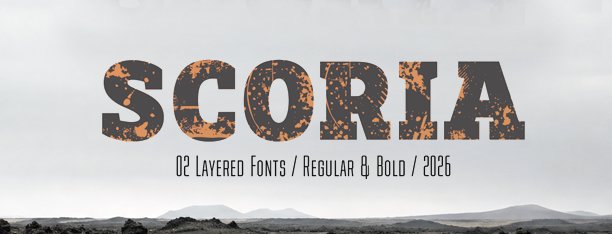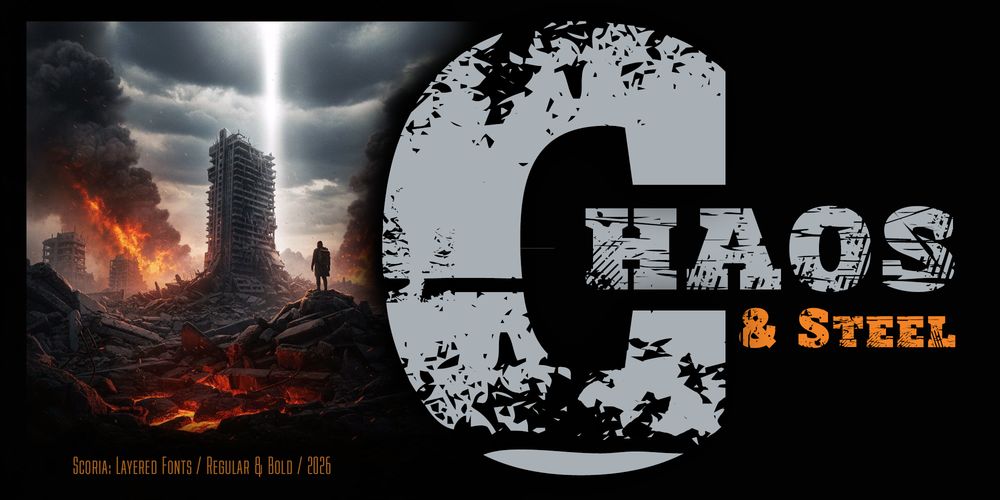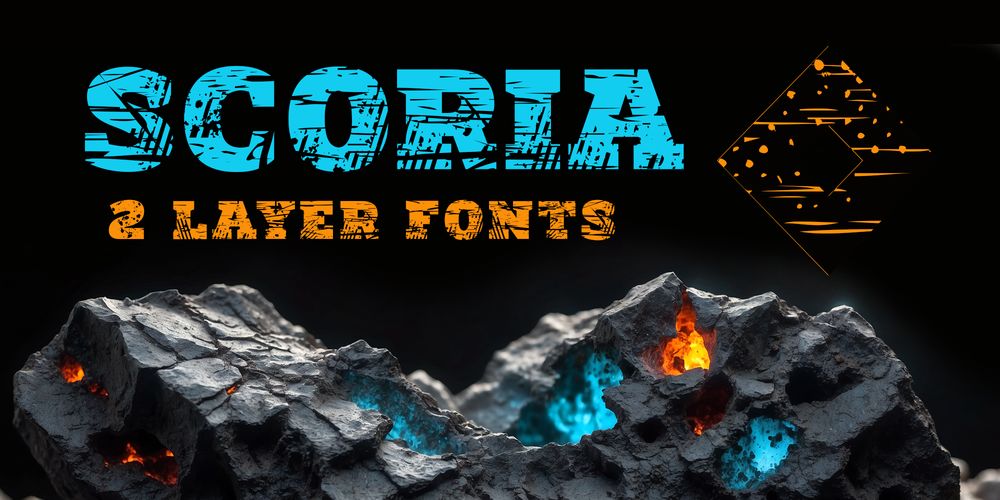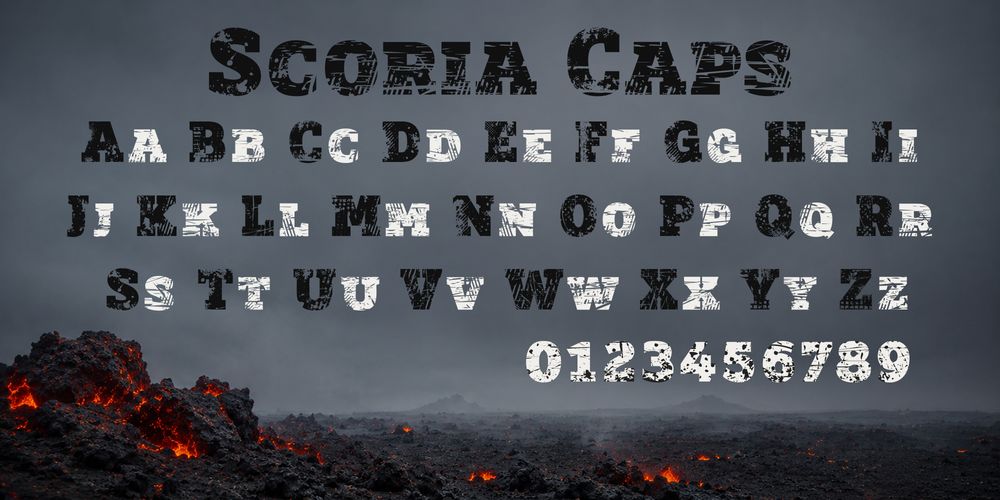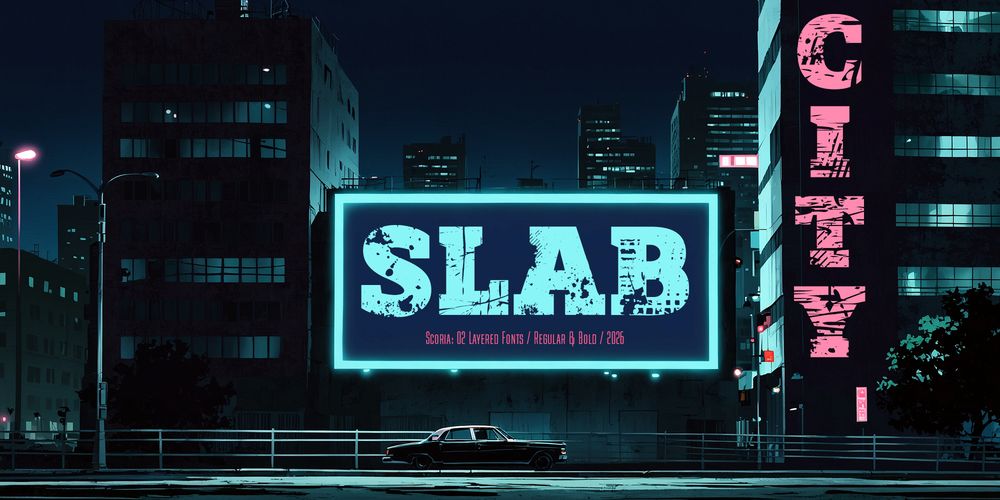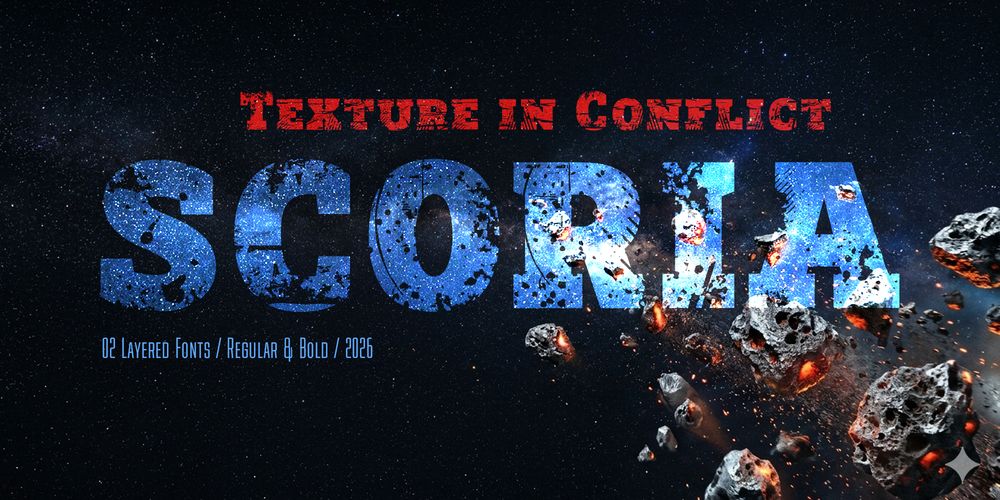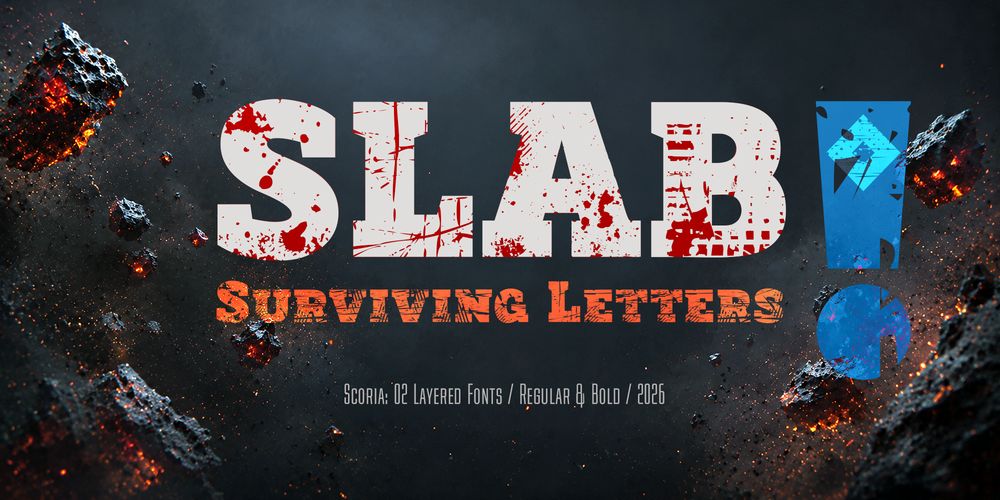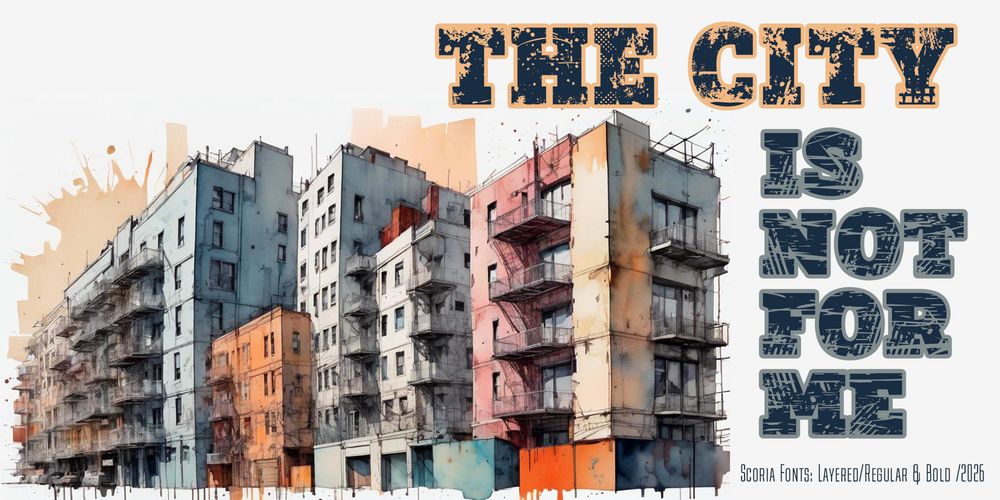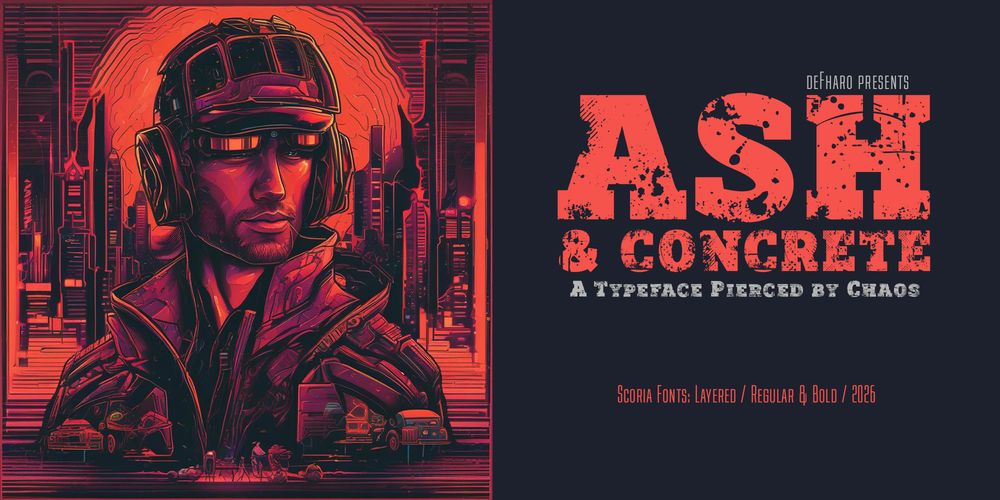
Su presencia es agresiva, pesada y profundamente expresiva, como un fragmento de arquitectura industrial sobreviviente a una catástrofe, ella grita desde las entrañas de la textura rota y erosionada. Cada letra parece cargar cicatrices, grietas y memoria.
Between structure & destruction.
Estilo: Slab Serif, Capitals, Display, Layered, Grunge
Proporción: Black
Tipografía nacida del colapso
Scoria nace como una reliquia tipográfica rescatada de un paisaje devastado de un mundo desgarrado. He creado esta fuente pensando en la belleza que aparece después del impacto, en las superficies erosionadas por el tiempo, el fuego y la fricción humana.
Su presencia es agresiva, pesada y profundamente expresiva, como un fragmento de arquitectura industrial sobreviviente a una catástrofe, ella grita desde las entrañas de la textura rota y erosionada. Cada letra parece cargar cicatrices, grietas y memoria, en una declaración de rebeldía tipográfica que se adapta a los contextos más intensos y urbanos, un símbolo de resistencia en medio del caos.
El ADN estructural
La base de Scoria parte directamente de la poderosa estructura de mi tipografía Biotrip Serif Caps Black, una de mis fuentes previas más rotundas. De ella conserva intacta su construcción sólida e impecable y una legibilidad excepcional, pero transformando por completo su superficie.
Scoria, combina la robustez de las serifas Slab con un estilo grunge que revela una historia de apocalipsis tipográfico, tragedias y naturaleza indomable. Sobre esa base Slab Serif de proporciones cuadradas, una textura profusa, rota y erosionada, transforma cada carácter en una pieza cargada de tensión y dramatismo, sin perder claridad ni impacto visual.
La poética del caos urbano
Scoria desafía la perfección pulida y uniforme, es una tipografía cuadrada, Grunge, Slab Serif, texturizada, erosionada y deliberadamente sucia. Su personalidad parece surgir de un entorno urbano colapsado: metal corroído, cemento fracturado, señales destruidas y superficies castigadas por décadas de conflicto. Quería que transmitiera la sensación de una tipografía que ha sobrevivido a algo violento, pero que aún conserva fuerza, carácter y presencia.
El estilo grunge celebra lo orgánico, lo callejero y lo desgastado, utilizando texturas pesadas y bordes carcomidos para inyectar una dosis de cruda realidad urbana en el diseño, introduce ruido, textura y desgaste humano. Scoria es el reflejo de esa corriente: pura actitud irreverente vestida de óxido y ceniza.
El poder de las capas: Títulos multicolores
Uno de los aspectos más especiales de Scoria es su sistema de 02 fuentes superpuestas (Layered Fonts). He diseñado las versiones Regular y Bold, como compañeras inseparables para funcionar juntas en superposición, permitiendo construir titulares puramente tipográficos en dos o más colores con un impacto visual enorme.
Este sistema abre la puerta a composiciones urbanas, experimentales y profundamente originales, ideales para diseños que buscan intensidad gráfica y personalidad propia.
No necesitas texturas externas ni efectos complejos: mi doble naturaleza crea composiciones urbanas, explosivas y profundamente originales. Es como si dos estados de un mismo espíritu hablaran al unísono, el propio texto se convierte en imagen, en capas de historia y color.
Lo que hay dentro del caos
A pesar de su apariencia salvaje, Scoria está armada con disciplina. Incluye dos versiones: Regular & Bold, además de flechas, signos y puntuación extra, junto a pequeñas formas amigables escondidas en medio del caos visual. También incorpora funciones OpenType avanzadas como ligaduras discrecionales, números alternativos con forma, Small Caps, Old Style Figures, etc. y múltiples detalles tipográficos diseñados para enriquecer la composición.
Todo ello con soporte completo para Latin Extended-A, para múltiples idiomas europeos.
Dónde deja huella
Scoria está hecha para el diseño editorial audaz, que no teme al riesgo, para folletos contundentes, posters que gritan, cartelería cinematográfica, branding de identidad fuerte, packaging que se resiste a ser ignorado y señalización que impone presencia.
Scoria no busca agradar en entornos sutiles; ha sido creada para dominar el espacio, dotando a tus diseños de una narrativa profunda, un impacto visual masivo y una personalidad que se niega a pasar desapercibida, y además no es una tipografía que pida permiso.